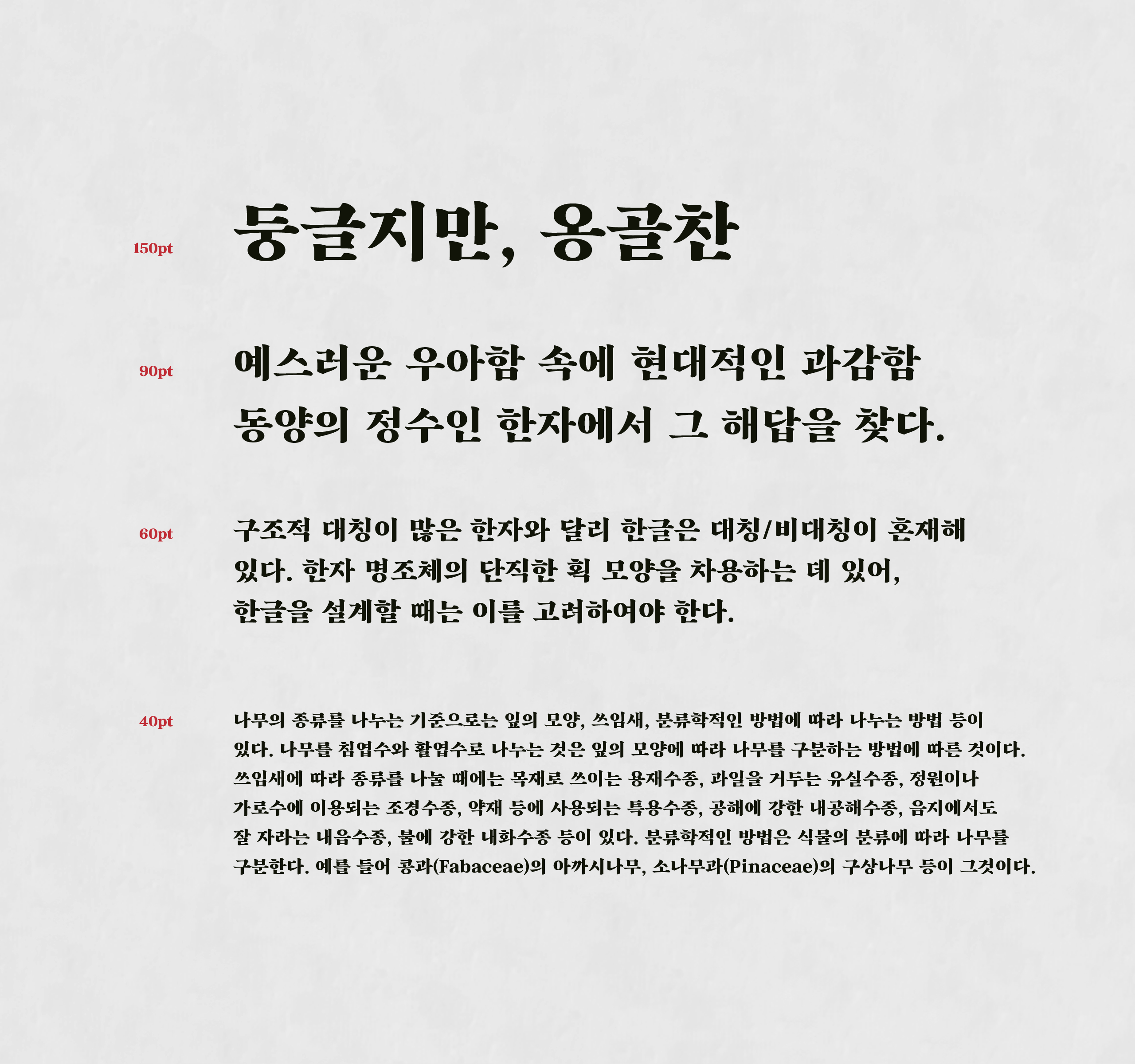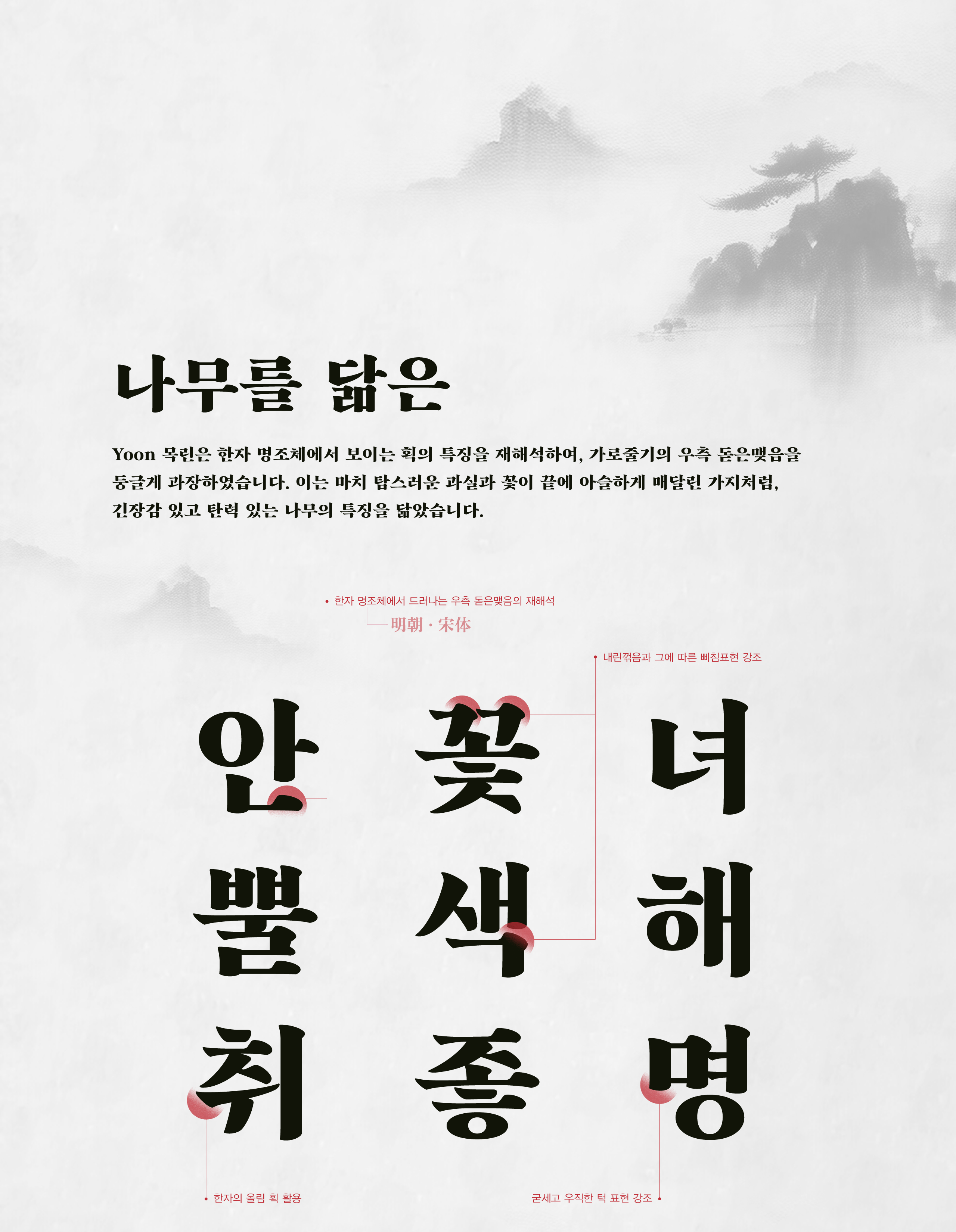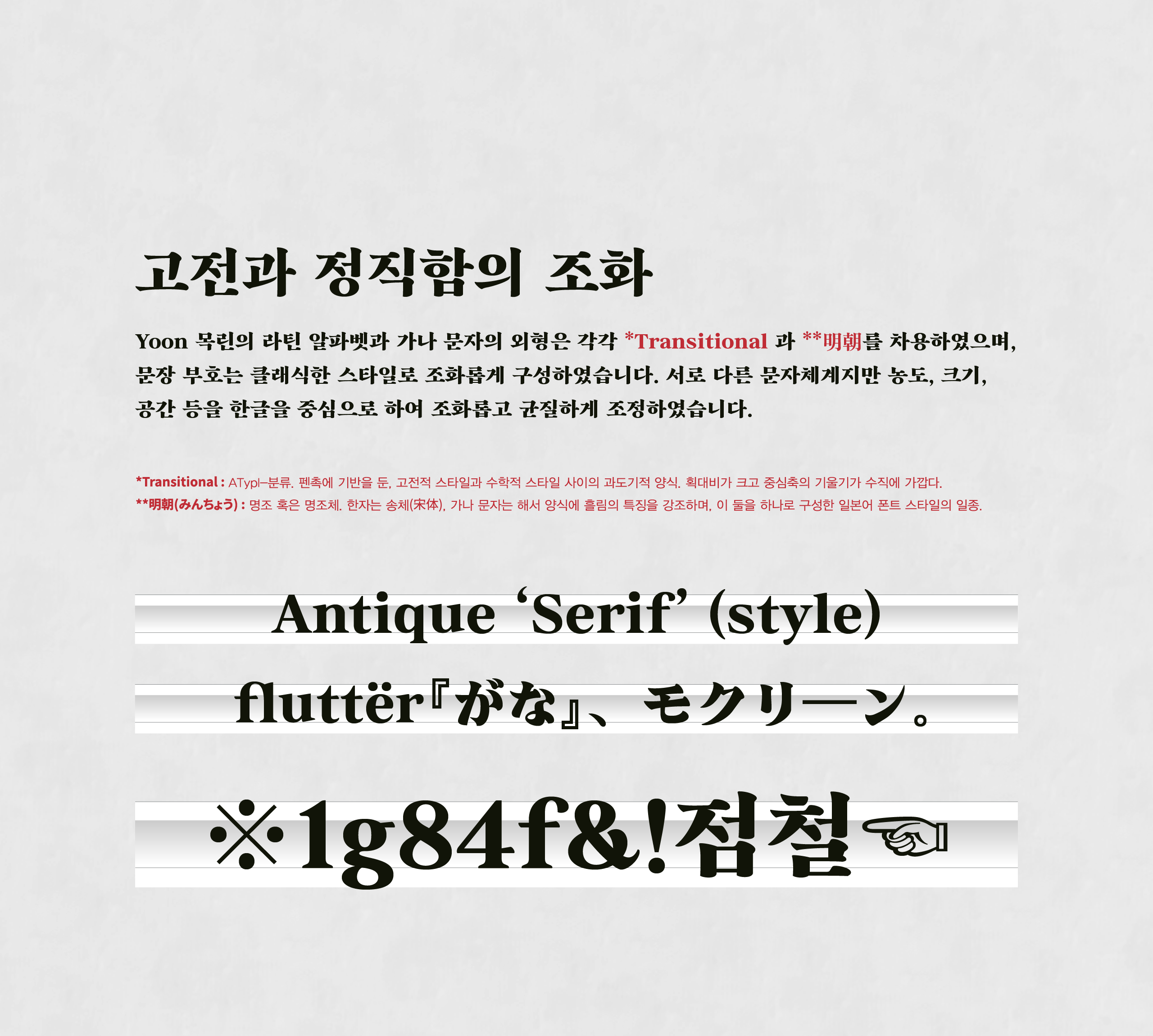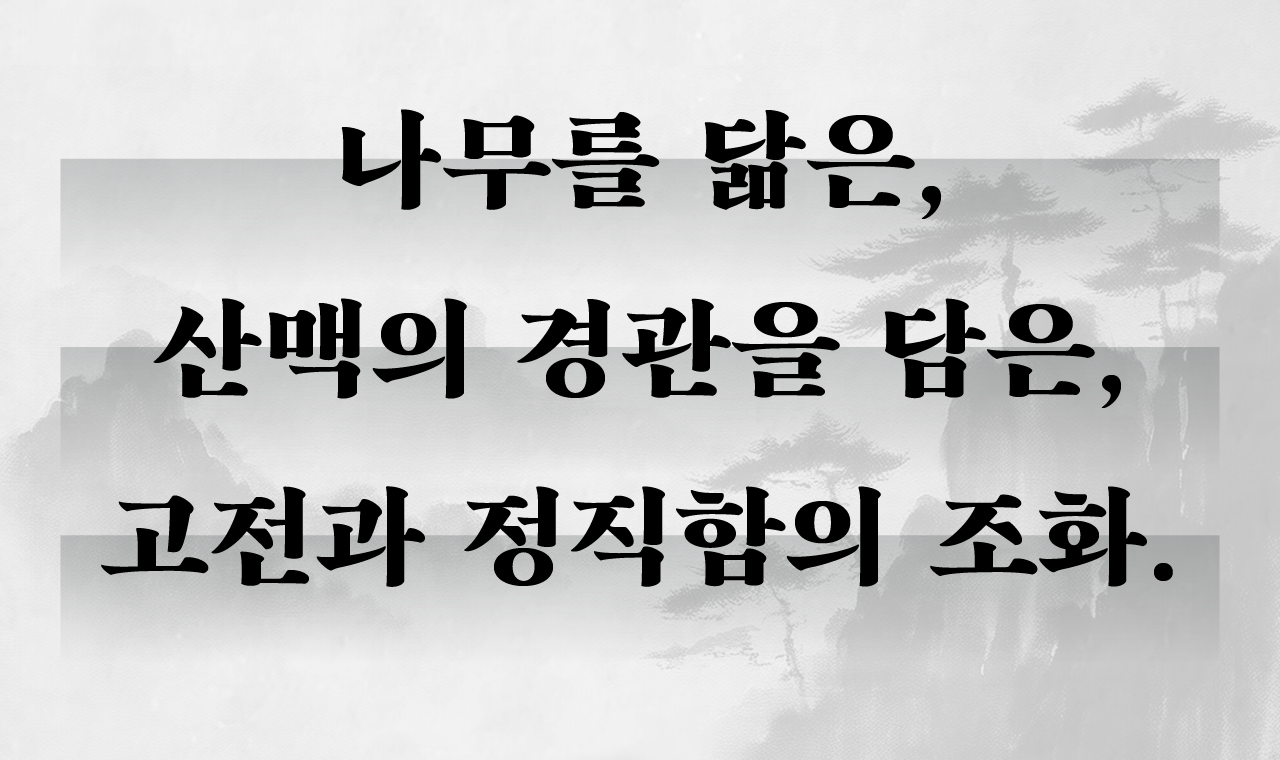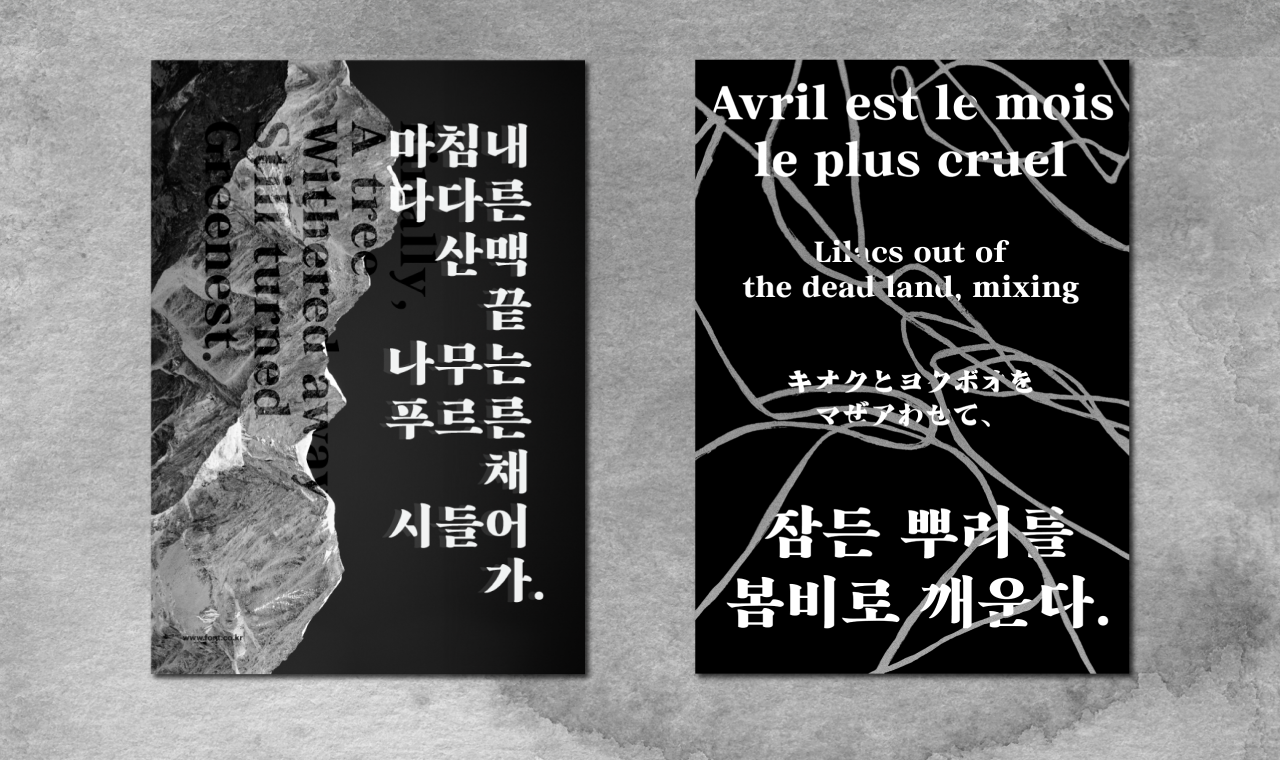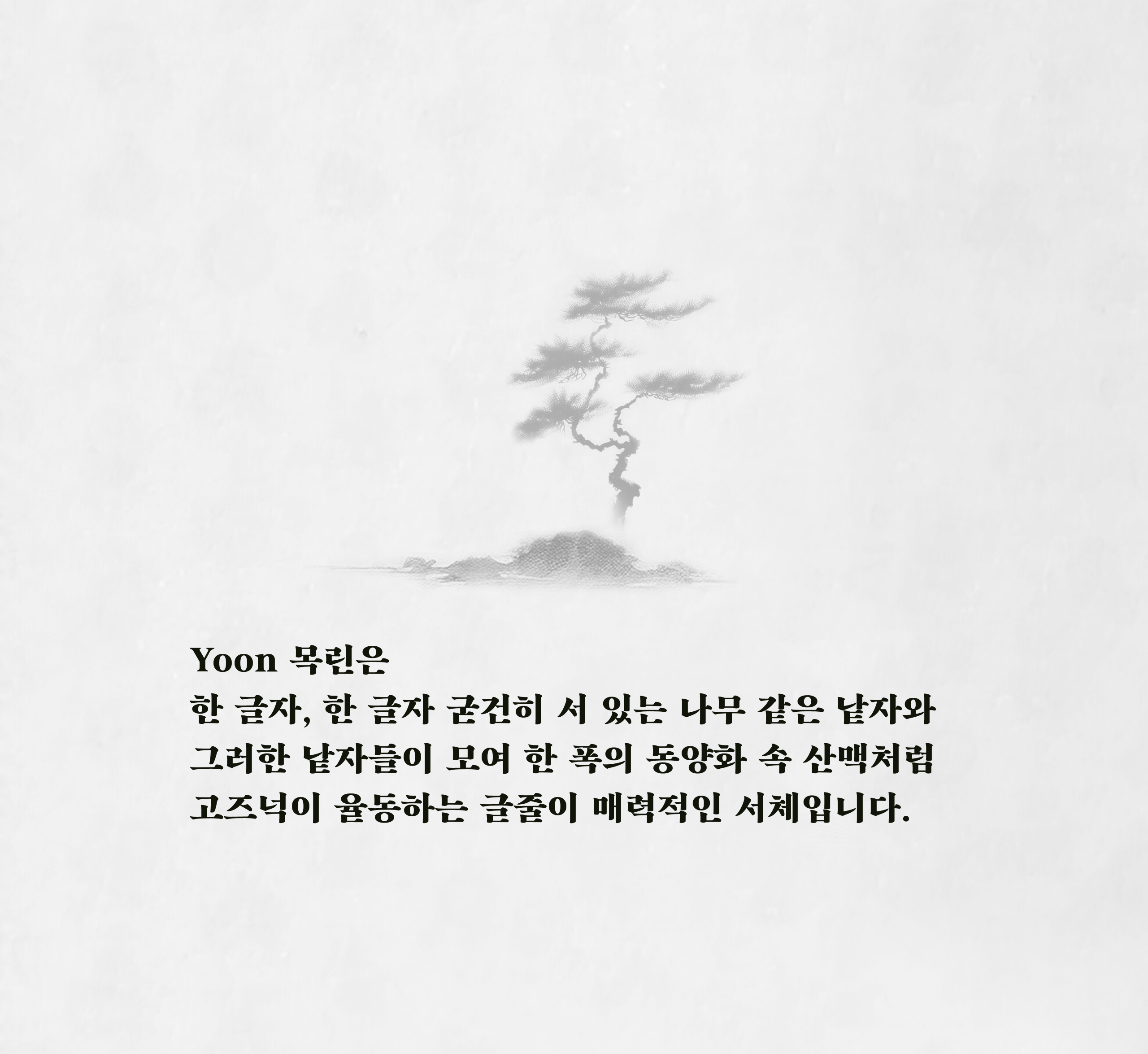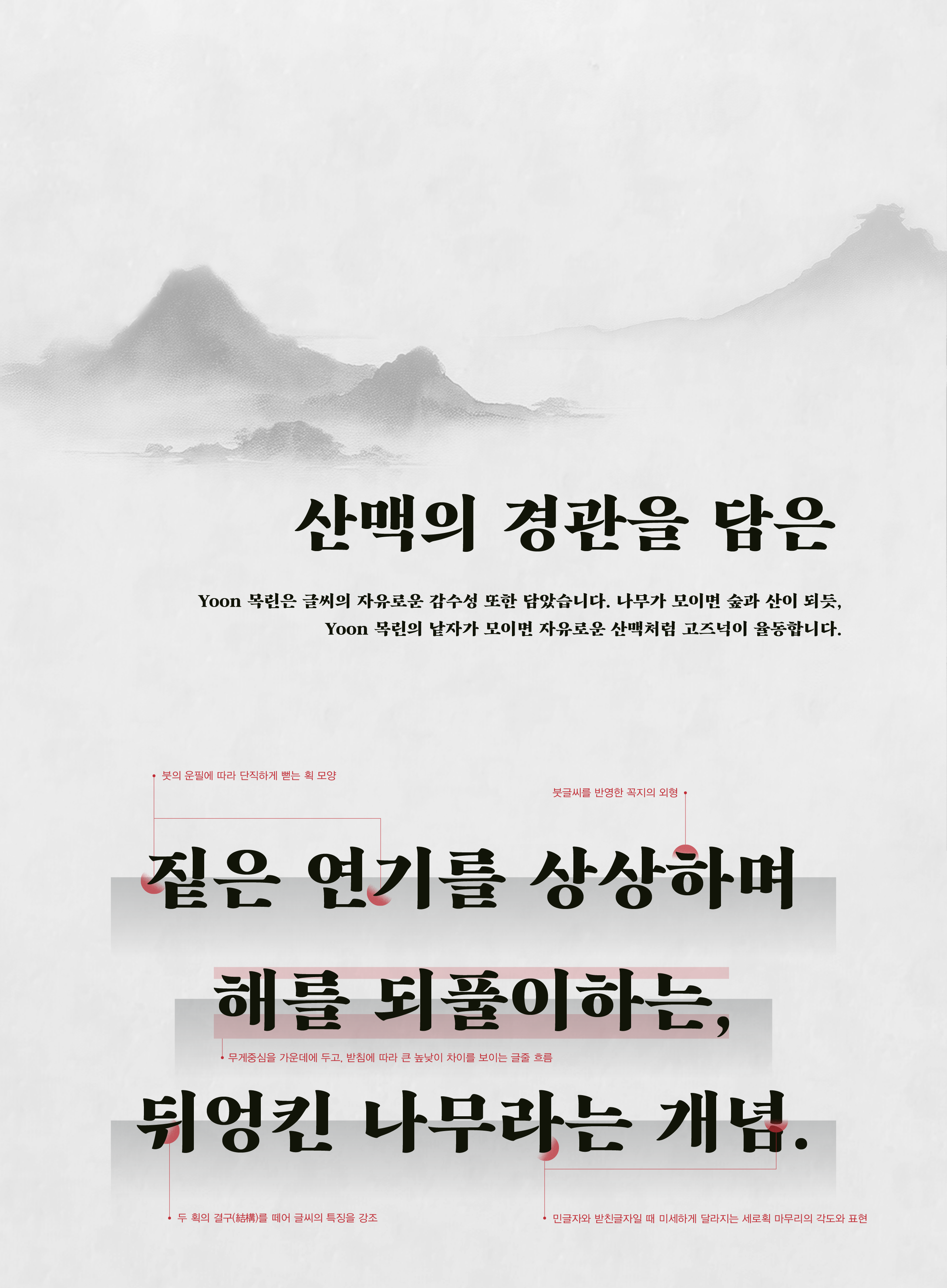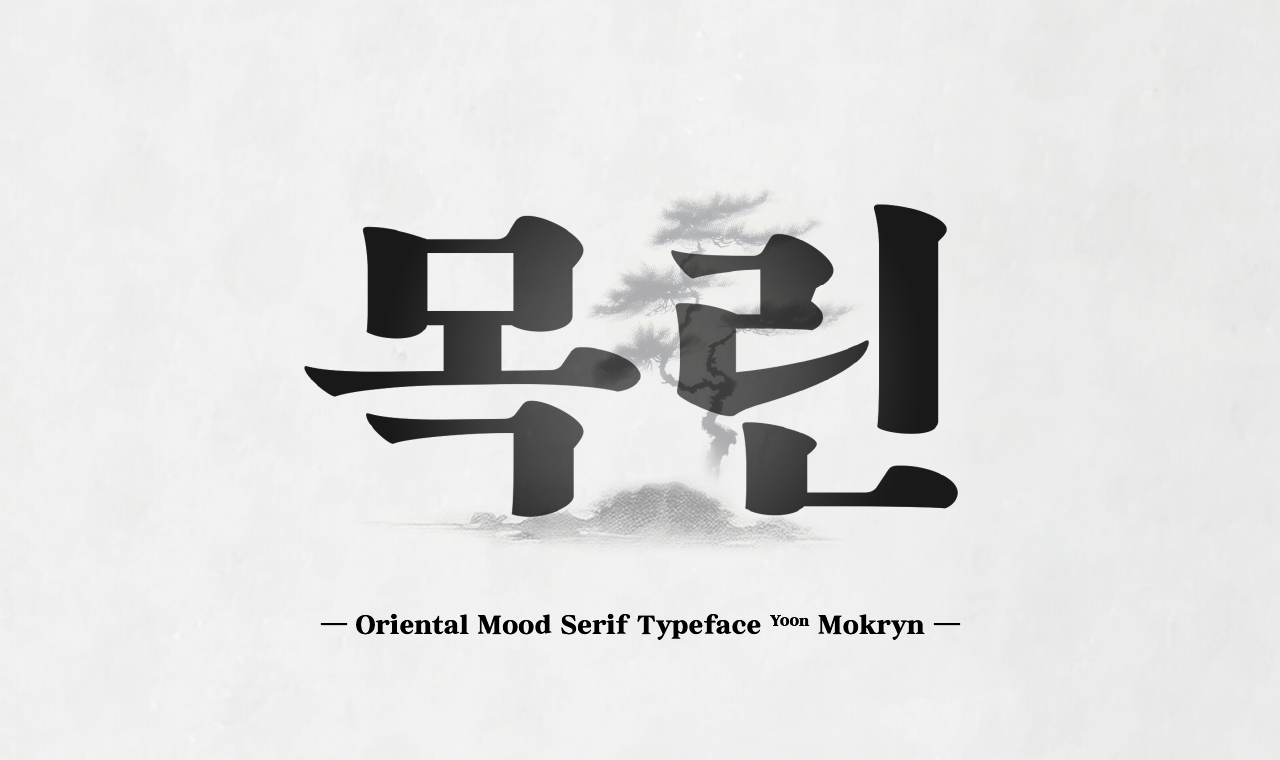
목린
2025
Yoon 목린
목린은 나무가 모여 산맥을 이루는 한 폭의 동양화 같은 고전적 인상의 제목용 서체입니다. 낱자는 큰 획 대비와 돋은 맺음의 강조로 나무처럼 굳세지만, 글줄은 글씨의 운필감과 리드미컬한 공간감이 드러나 산맥처럼 고즈넉이 율동합니다. 크고 여유로운 공간에 시각적 주목이 필요한 매체에 사용하기에 적합합니다.
한글 2,780자 / 라틴 95자 / KS약물 986자
송우빈